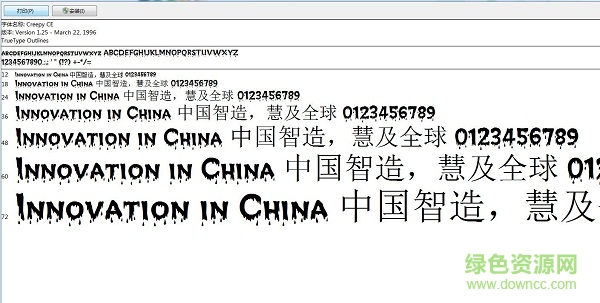
creepy ce
creepy ce字體是一款字形設(shè)計(jì)非常獨(dú)特的英文個(gè)性字體,沒字體帶有黑點(diǎn),就像是下雨一樣,視覺上很醒目,可以用在電影海報(bào)設(shè)計(jì)或是平面設(shè)計(jì)方面,效果非常棒,歡迎大家在綠色資源網(wǎng)免費(fèi)下載該字體,
creepy ce字體